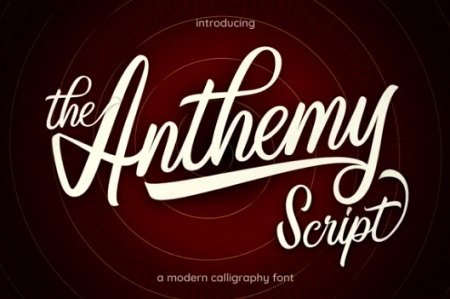
Anthemy Font
Anthemy é uma fonte manuscrita agradável e assertiva. Esta fonte tem uma leitura forte, confiante e dinâmica e pode adicionar toneladas de caráter nostálgico aos seus designs. Anthemy é codificado em PUA, o que significa que você pode acessar todos os glifos e traços com facilidade!
Anthemy Font